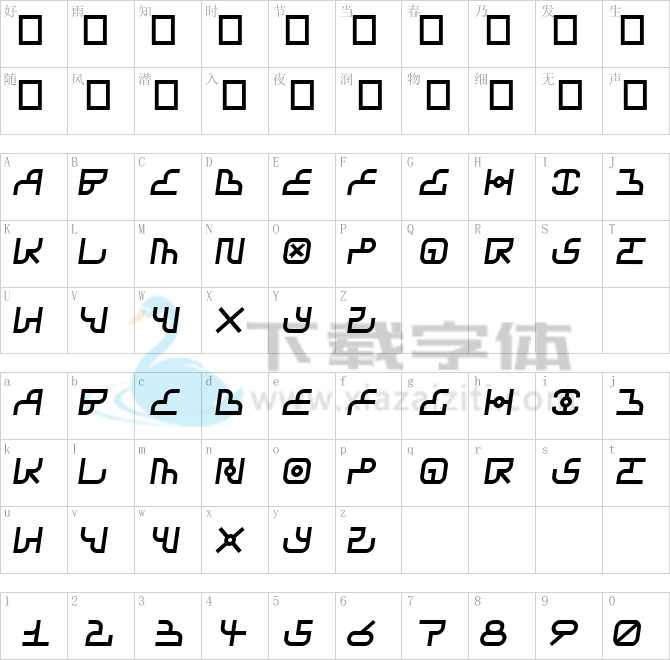
Airbag Street.ttf字体下载,这款字体结构工整、笔画清晰,兼顾美观与易读性,适用于标题、正文、海报、包装、LOGO 等多种场景。字形优雅稳定,风格百搭耐看,适配日常排版与创意设计,让文字呈现更舒适、更具质感。Airbag Street.ttf字体下载一笔一画,皆是细节,以均衡的比例、流畅的线条打造舒适视觉体验,字形端正大气,风格简约现代。无论是商业设计、品牌宣传还是日常排版,都能轻松驾驭,让文字更有格调与力量。Airbag Street.ttf字体下载字体下载。